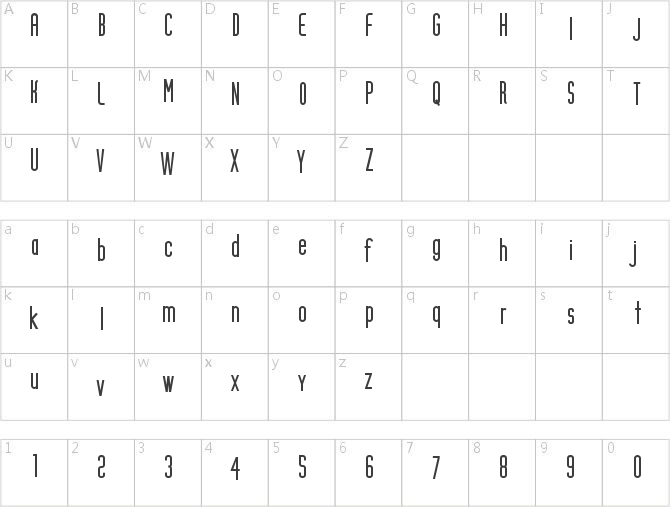
字体名称: CFCraig
CFCraigRobinson-Regular
CFCraigRobinson-Regular介绍
CFCraigRobinson-Regular字体字库是一款让人赏心悦目、百看不厌的英文字体,适合各类广告和产品包装设计应用,字体大小0.02MB,格式为ttf字体,上传用户是凡尘之间,作者/版权方为未知